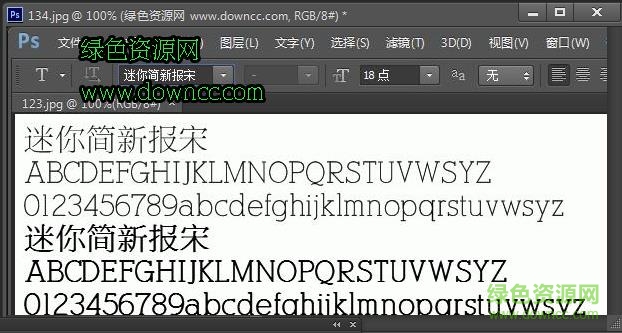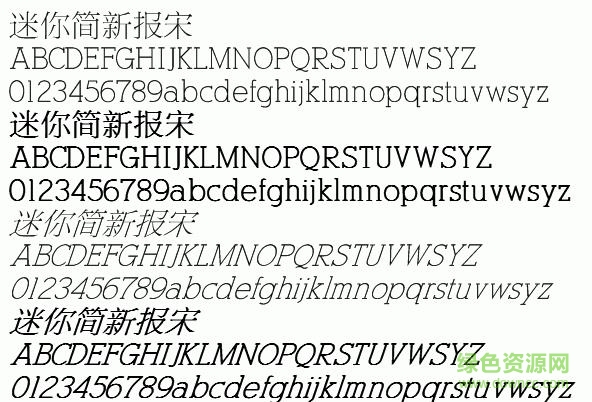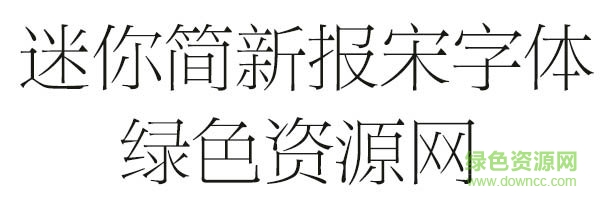
迷你簡新報宋字體
迷你簡新報宋字體運(yùn)用到各類文件制作中讓你能夠制作出好看的字體效果,營造出優(yōu)質(zhì)的視覺效果,用戶能夠?qū)ζ涮砑痈黝愄厣Ч?,如加粗傾斜,藝術(shù)效果等!
特色介紹
這個字體筆畫有粗細(xì)變化,而且一般是橫細(xì)豎粗,很適合廣告設(shè)計、平面設(shè)計、印刷包裝、正文標(biāo)題等人員使用。